Blendings machen jeden Schriftzug zu einem absoluten Hingucker! Deshalb zeige ich dir jetzt, wie du die buntesten Farbverläufe malen kannst. Ganz ohne welliges Papier und harte Farb-Ränder.
Was du für das Blending brauchst
Bevor wir starten, hier noch eine schnelle Materialkunde:
Der wichtigste Trick ist die Nutzung von hochwertigem Aquarell- oder Mix-Media-Papier. Nur damit gelingen perfekte Blendings.
- Aquarell- oder Mix-Media-Papier (300g)
- Wassertankpinsel
- Brushpens in passenden Farben
- Einen hellen Brushpen des gleichen Farbspektrums
Das wars auch schon. Alles andere ist optional (zum Beispiel Skizzen, Hilfslinien und die strategische Entwicklung, die du aus meinem Kurs kennst).
Ich nutze gerne Karin Brushmarker oder Tombow ABT Dual Brush Pens für meine Verläufe.
Schritt 1: Schreibe das Wort mit einem hellen Brushpen vor
Die helle Grundierung ist unsere Schablone für das komplette Blending. Du könntest hier auch mit einem hellen Grau arbeiten, dies führt aber meist zu einer Entsättigung der Farben.
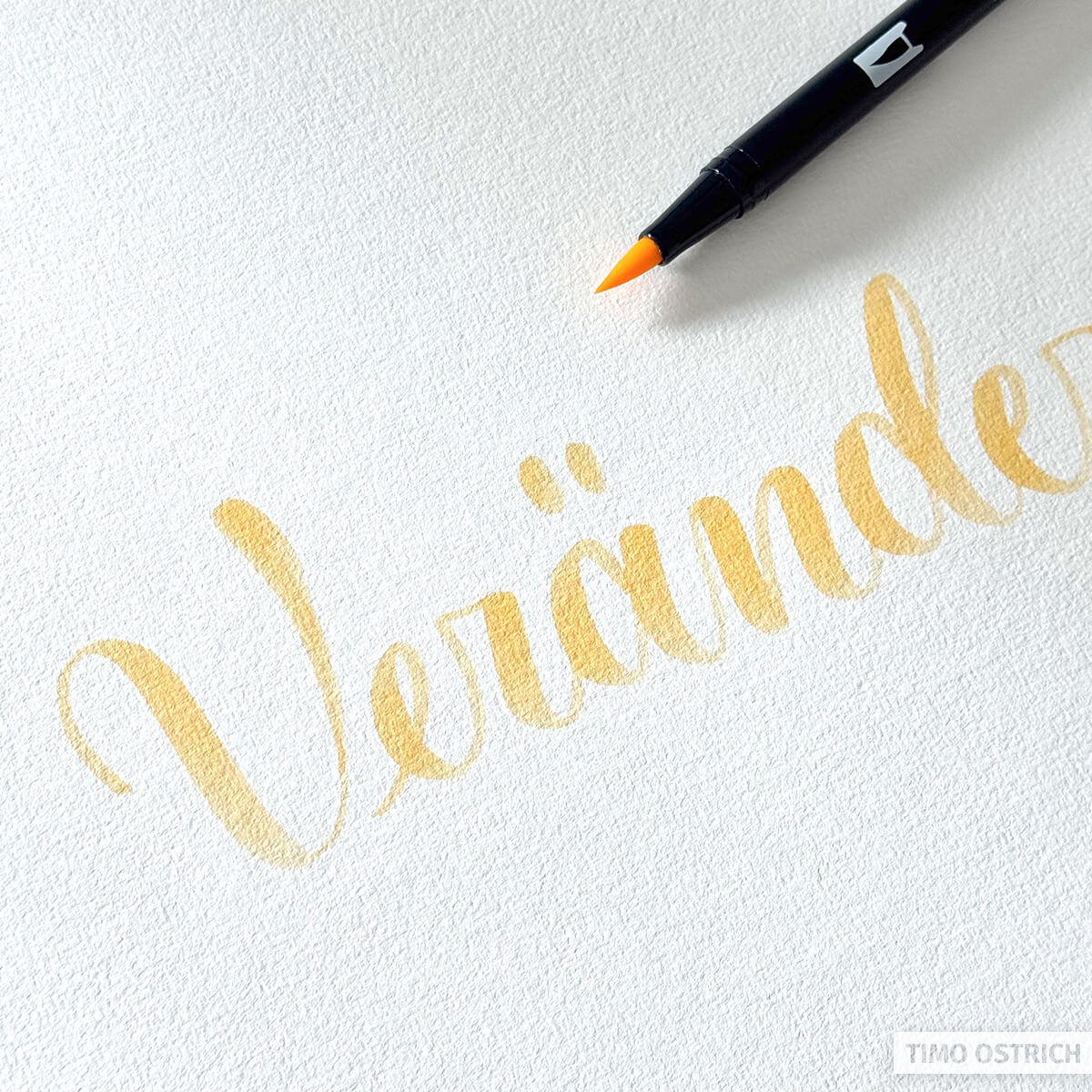
Schritt 2: Trage weitere Farbschichten auf
Nun trägst du weitere Farbschichten auf. Du kannst mit dieser Blending-Technik (fast) beliebige Farben mischen. Sie sollten jedoch zum Farbton der Grundierung passen. Fange dazu mit dem ersten Buchstaben an.
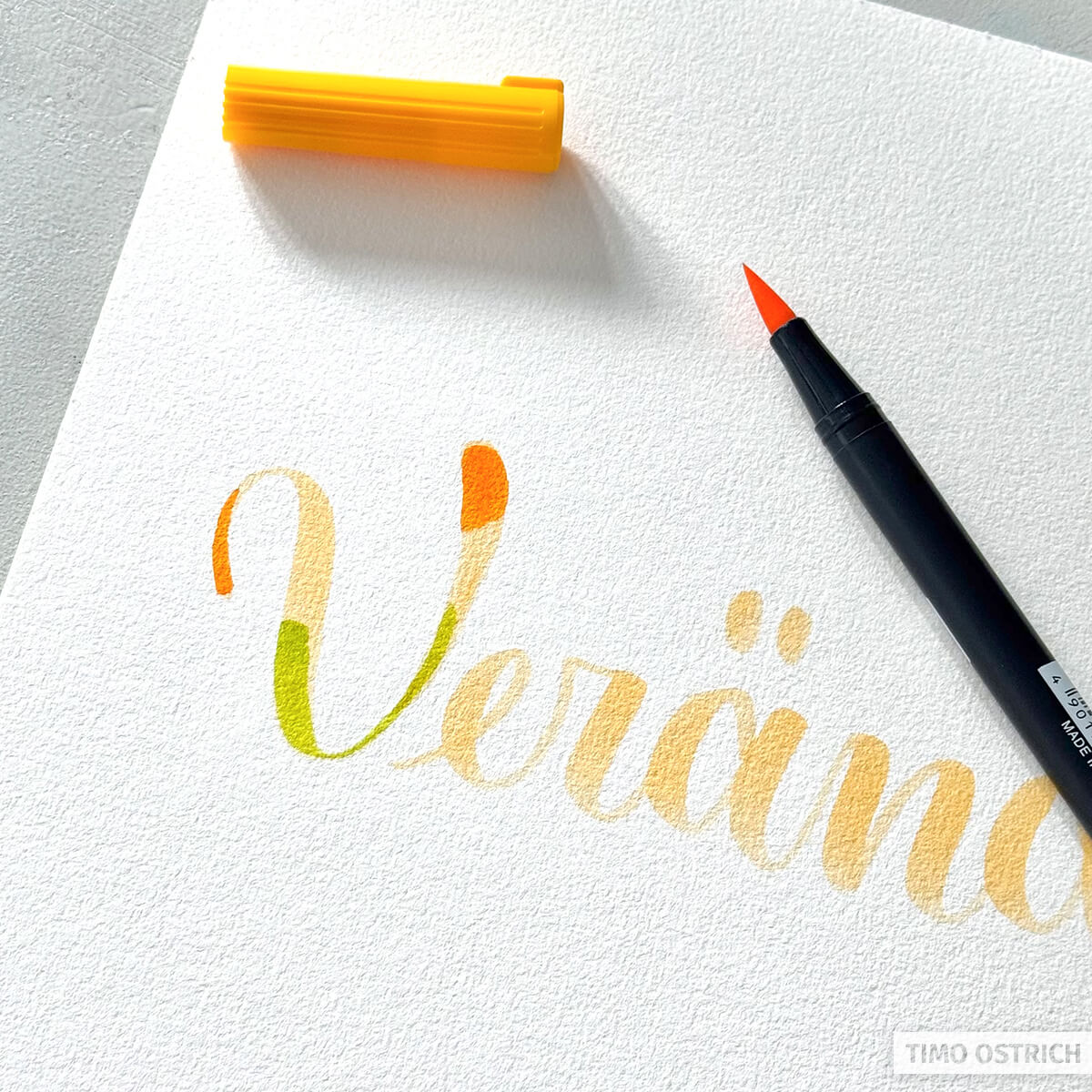
Schritt 3: Farben vermischen
Nun folgt das eigentliche Verblenden der Farben. Dazu nutzt du einen Wassertankpinsel.
Achte darauf, nicht zu viel Wasser zu verwenden und halte dich an deine Schablone.
Mit mehreren Pinselstrichen verwischst du nun die harten Übergänge zwischen den einzelnen Farbaufträgen.
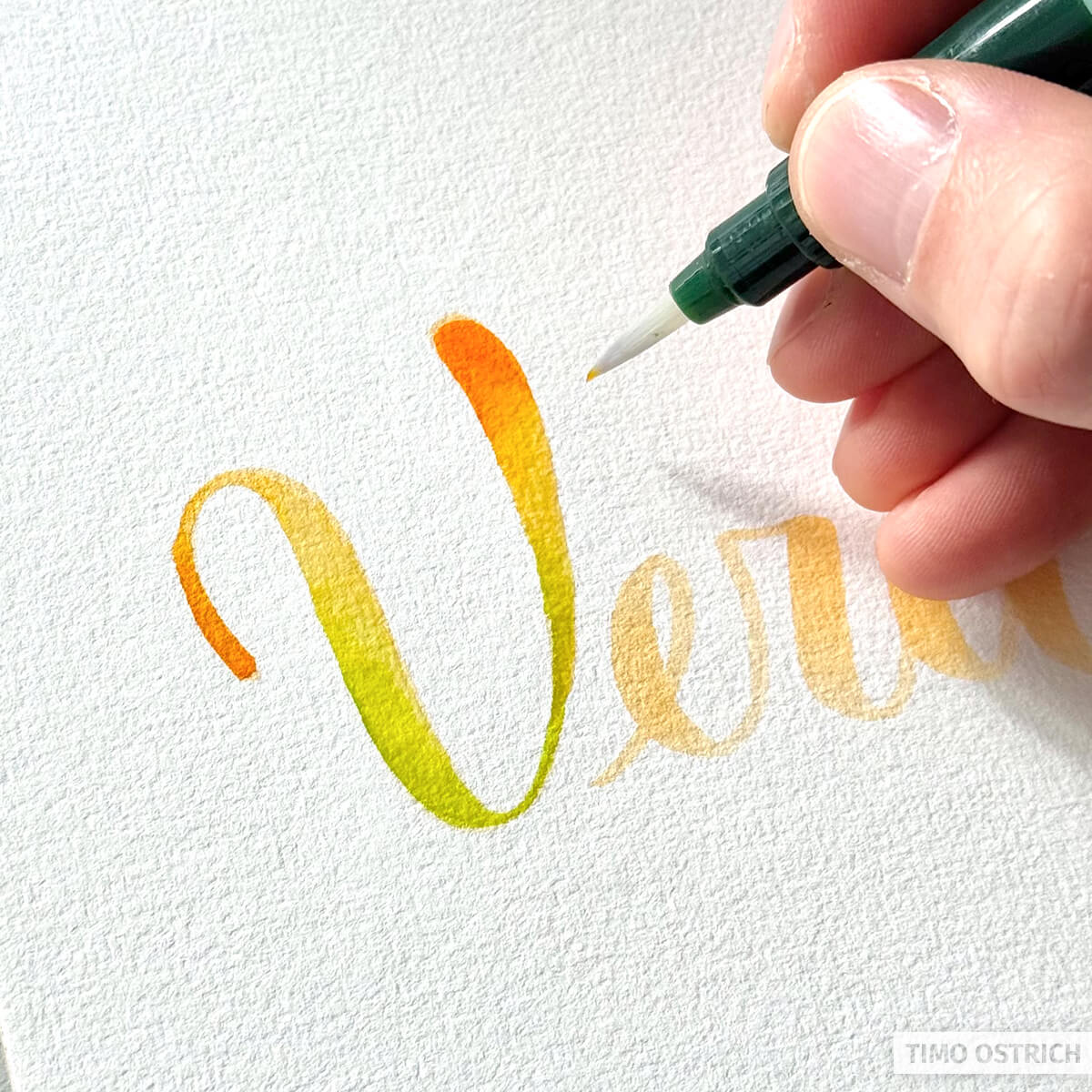
Schritt 4: Buchstabe für Buchstabe vorgehen
Wichtig ist, dass du jetzt Linie für Linie und Buchstabe für Buchstabe vorgehst. Trägst du erst alle Farben auf das ganze Wort auf, lassen sich die Kanten kaum noch sauber verblenden.
Ist der Farbauftrag jedoch frisch, gelingt das ziemlich locker und du kannst die Farben fließen lassen! Fast wie beim richtigen Aquarellieren.
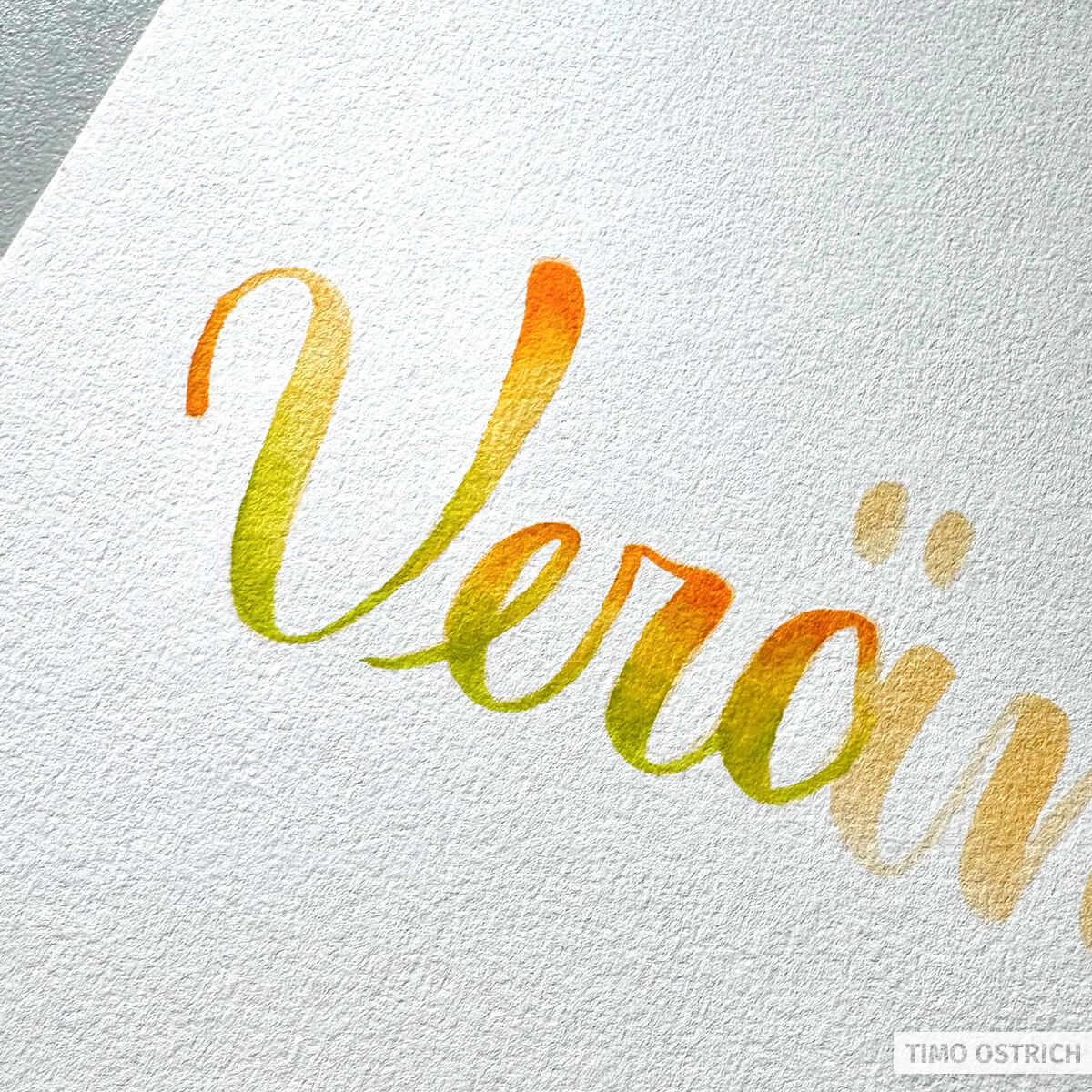
Schritt 5: Das komplette Wort ausfüllen
Behalte deine Technik das ganze Wort über bei und es entsteht ein gleichmäßiger Verlauf. Alternativ kannst du natürlich die Farben verändern oder die Richtung anpassen. Der Kreativität sind wie immer keine Grenzen gesetzt. Yippie! 🥳
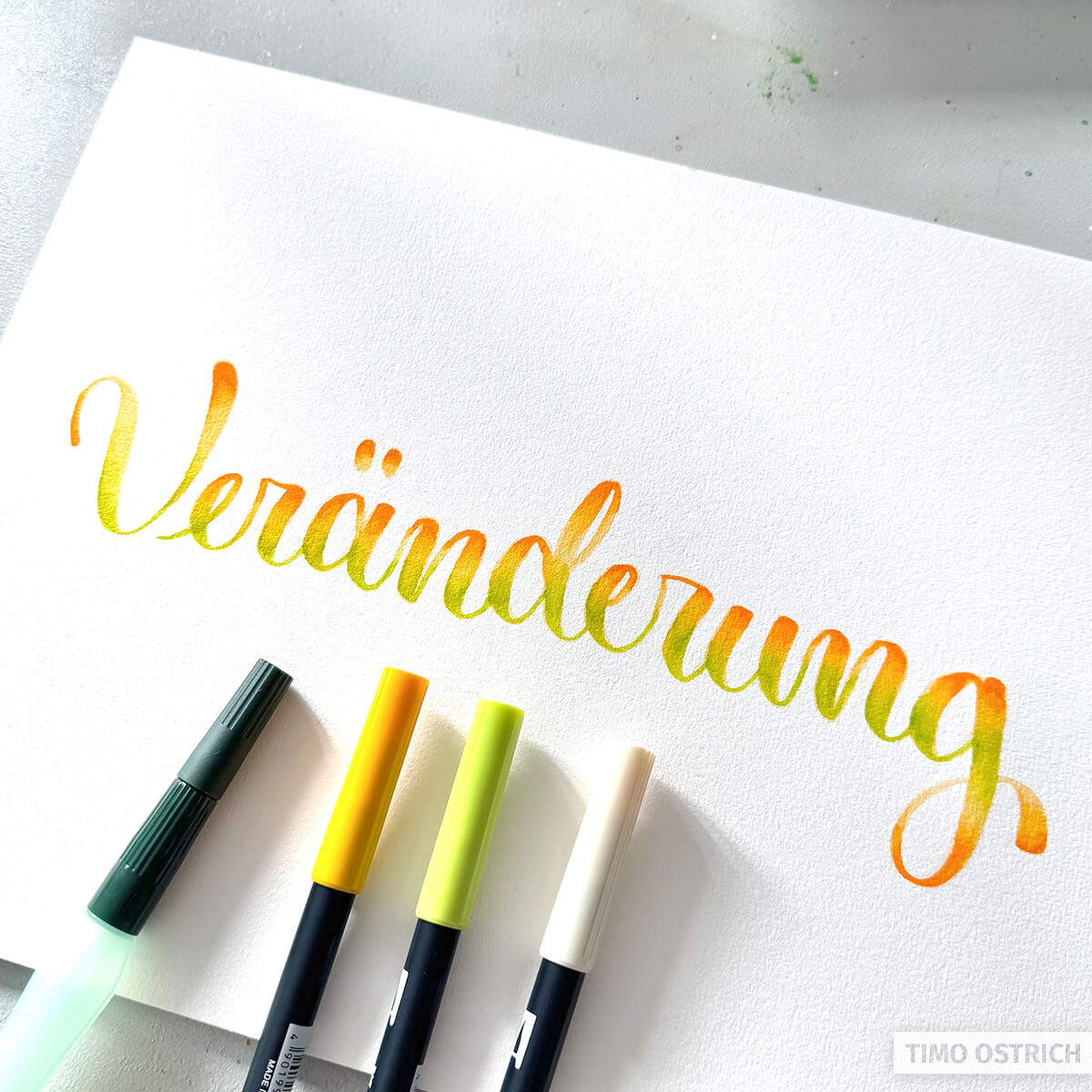
Bonus: Weitere Beispiel-Blendings aus meiner Feder
Und wie könnten solche Farbverläufe noch aussehen? Hier ein paar Beispiele aus meinen unzähligen Handletterings der letzten Jahre: